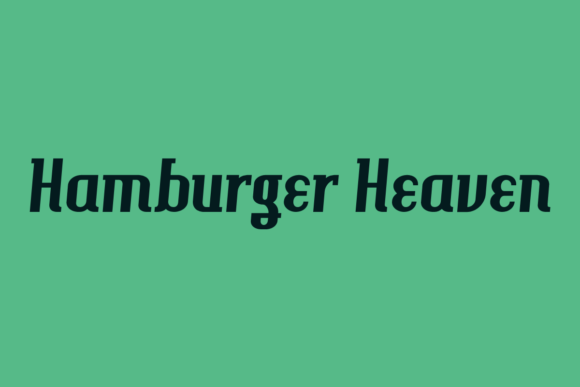
Hamburger Heaven
Ulasan Lengkap Hamburger Heaven: Font Vintage yang Membuat Desain Anda Berkilau
Jika Anda sedang mencari font yang memberi kesan retro sekaligus elegan, Hamburger Heaven adalah pilihan yang tak boleh dilewatkan. Dirancang oleh Nick Curtis, font serif ini menggabungkan nuansa vintage dengan kejelasan baca yang modern, menjadikannya sempurna untuk berbagai aplikasi kreatif.
Kenapa Hamburger Heaven Patut Dipertimbangkan?
- Gaya Vintage yang Khas – Garis-garis serif yang tebal dan proporsi klasik menciptakan atmosfer retro yang kuat, cocok untuk proyek dengan tema nostalgia.
- Fleksibilitas Tinggi – Cocok dipakai pada quotes, kaos, headline, koran, iklan, fashion, majalah, logo, frame art, kartu pernikahan vintage, dan banyak lagi.
- Keterbacaan Optimal – Meskipun memiliki detail dekoratif, setiap huruf tetap jelas dibaca pada ukuran kecil maupun besar.
- Desain Elegan – Kombinasi tebal dan tipis pada huruf memberikan keseimbangan visual yang memikat, ideal untuk memperkuat identitas merek.
Ide Penggunaan Hamburger Heaven dalam Proyek Anda
- Poster & Flyer – Tambahkan judul utama dengan Hamburger Heaven untuk menonjolkan pesan utama.
- Desain Kaos – Buat slogan retro yang eye‑catching pada kaos vintage.
- Kartu Undangan Pernikahan – Sentuhan klasik pada kartu pernikahan bergaya old‑school.
- Logo Brand – Gunakan huruf kapital tebal untuk menciptakan logo yang kuat dan mudah diingat.
- Layout Majalah & Blog – Pasang sebagai heading artikel untuk menambah nilai estetika.